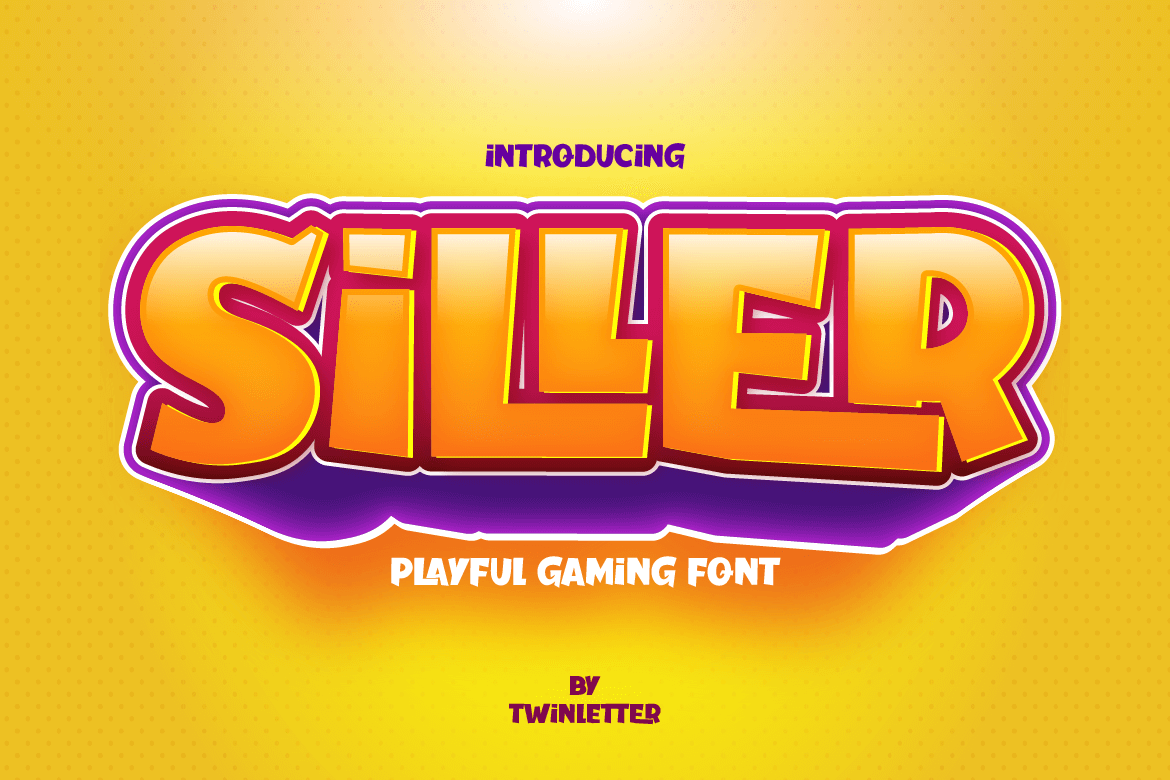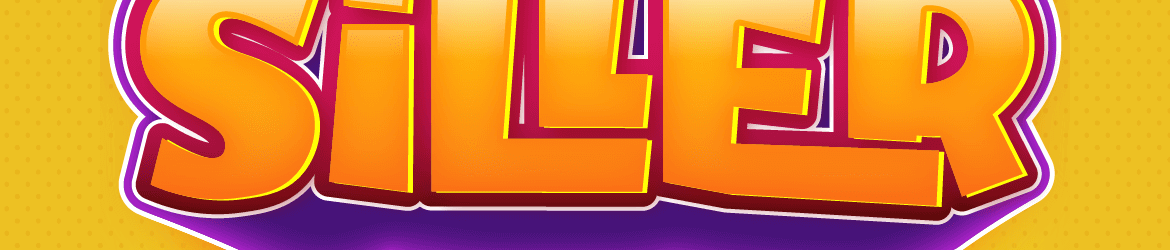
A Siller Font é uma fonte display divertida e alegre criada por twinletter. Ideal para aplicativos de jogos que buscam despertar uma atmosfera lúdica e aconchegante, essa fonte combina um toque leve e descontraído com o estilo mais sério necessitado por projetos oficiais. Perfeita tanto para ambientes corporativos quanto para criações pessoais, ela se destaca como uma escolha perfeita para qualquer projeto direcionado a crianças ou adultos. Combinando simplicidade com beleza, a Siller Font é um recurso visual atraente para projetos que precisam de um toque jovial e atemporal. Engajante e versátil, ela se torna uma escolha inteligente para designers e criativos em busca de um elemento gráfico inovador e divertido.